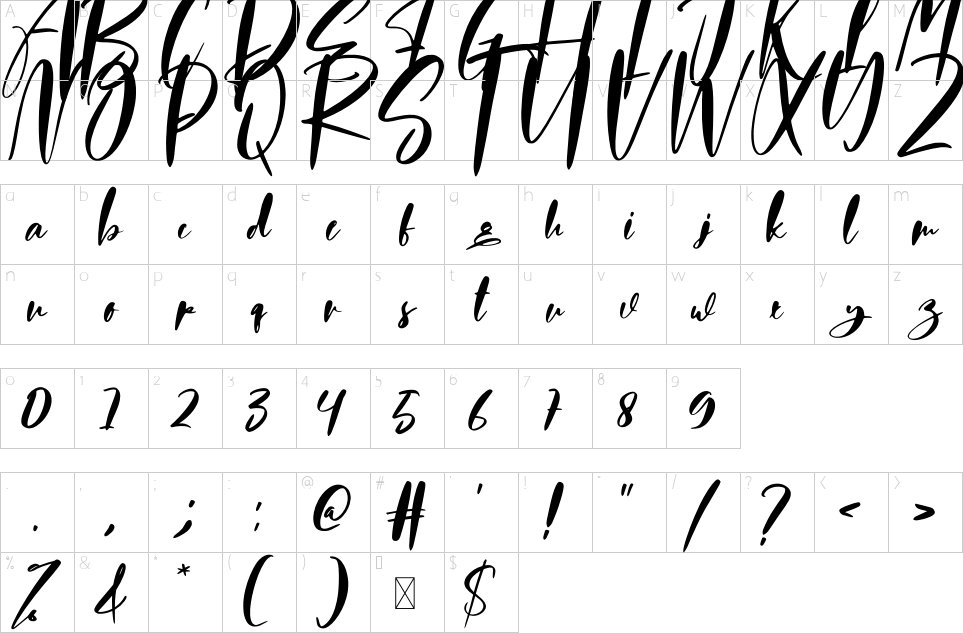
Esta página de download apresenta a Photographer font, uma elegante fonte gráfica projetada especificamente para profissionais de fotografia. Desenvolvida por scratchones, esta font é perfeita para criar efeitos gráficos impressionantes, desde pequenos detalhes de texto até grandes títulos de capa. Com sua abrangente gama de caracteres e linhas distintas, Photographer atende às necessidades de fotógrafos que precisam de uma font que seja tanto atraente quanto funcional. Com apenas um clique, você pode adicionar um toque de sofisticação a qualquer projeto de foto ou design de imagem. Download Photographer font agora e aumente a qualidade de seus trabalhos de fotografia.